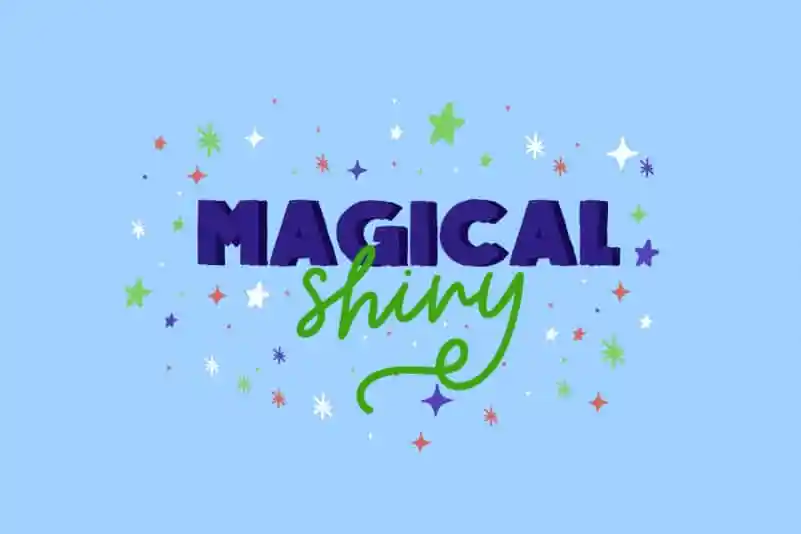
Magical Shiny Script Font
Magical Shiny Script Font é uma opção única para designers que buscam adicionar uma dose extra de atração às suas criações digitais. Esta dupla de fontes, ideal tanto para uso no display quanto como script personalizado, é perfeita para qualquer projeto que desejem desenvolver — seja uma marca, embalagem de produto, convite, citação, camiseta ou até mesmo um cartaz. Os designers têm a oportunidade de explorar o potencial desta fonte em projetos criativos como ilustrações infantis, banners e logos, pois Magic Shiny Script é particularmente adequada para temas infantis quando combinado com cores brilhantes. A sugestão da descrição original sugere uma utilização única que vai desde a criação de um cartaz educacional até os detalhes mais sutis em camisetas personalizadas. Essa fonte é perfeita para aqueles que buscam uma fonte versátil e criativa, especialmente para uso no design gráfico. Ela oferece uma ótima combinação de suavidade e flexibilidade, adequada tanto para aplicações digitais quanto para impressão em alta qualidade. O Magical Shiny Script Font não é apenas uma fonte, mas também um complemento perfeito para qualquer projeto que busque uma mistura única e atraente. O brilho sutil e a leveza da fonte garantem que seus projetos se destaquem, tornando-o uma escolha certa para designers buscando adicionar um toque especial em suas criações.